50 крутых бесплатных шрифтов
Для создания действительно крутых проектов иногда не хватает одной важной детали — хорошего шрифта. В этой подборке вы можете посмотреть и скачать 50 самых популярных шрифтов, которые сделают вашу работу лучше.
Кириллица
Bravo
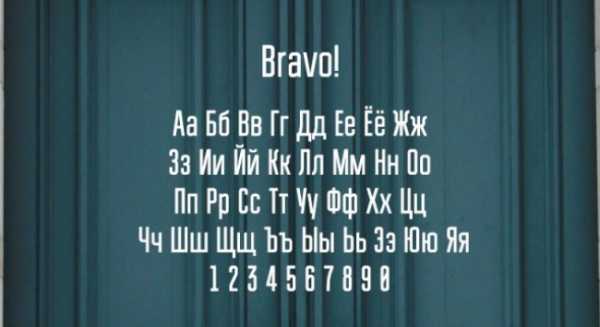
Yanone Kaffeesatz
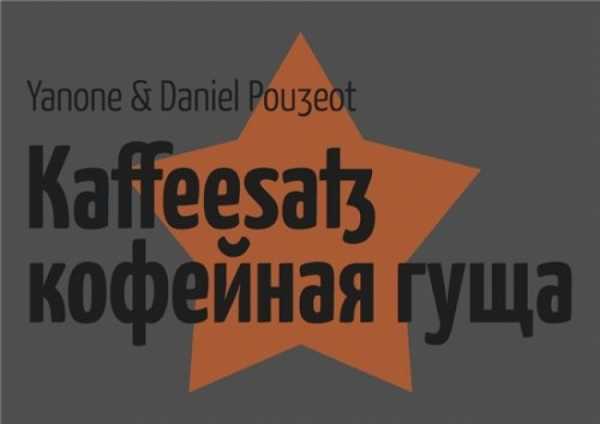
BadScript
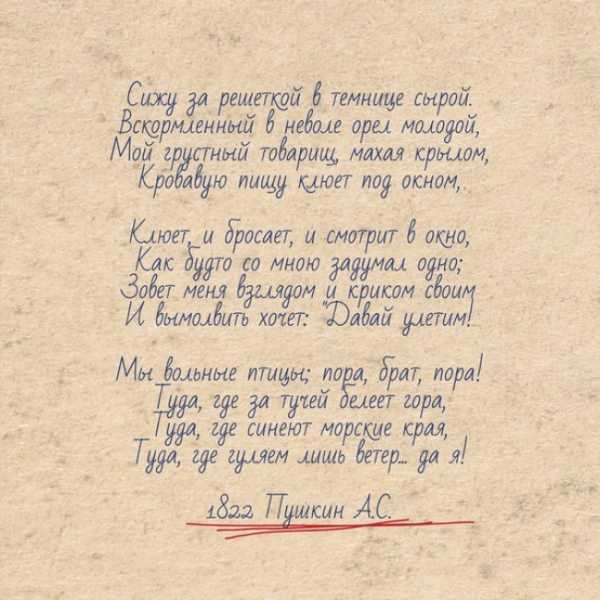
Nord
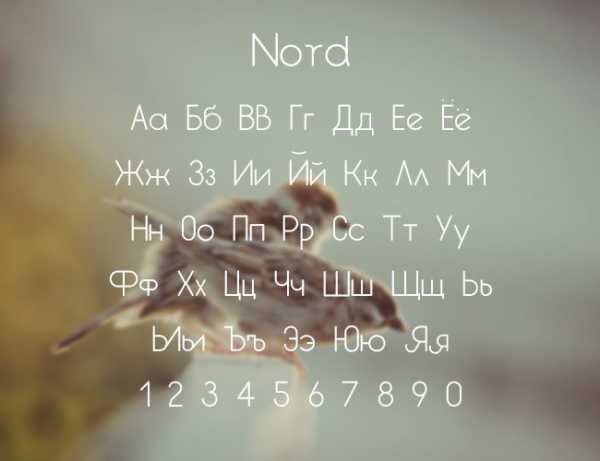
Intro Condensed
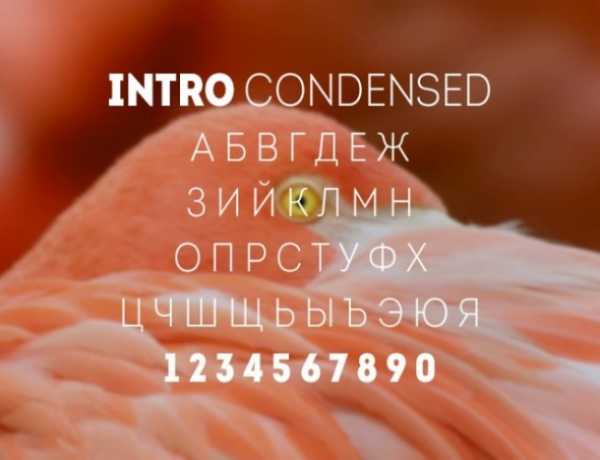
Ropa Sans
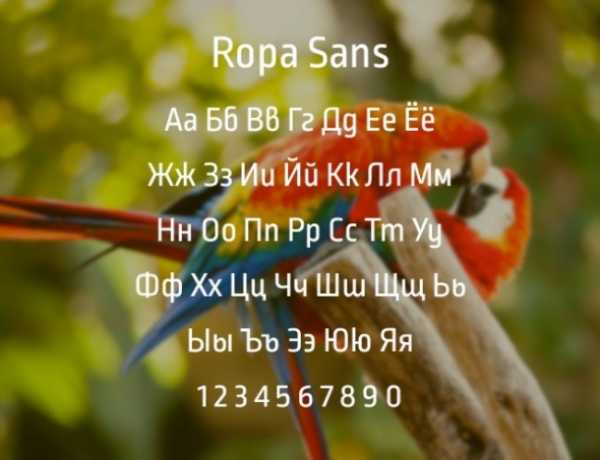
Centar Sans
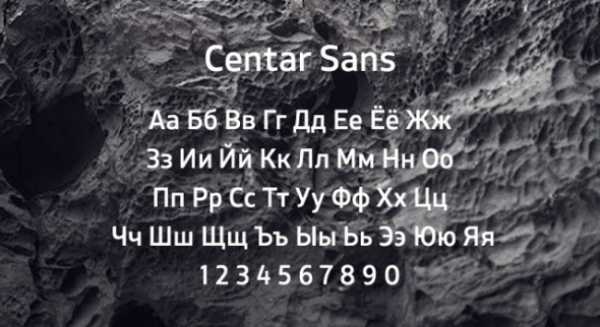
Lighthaus
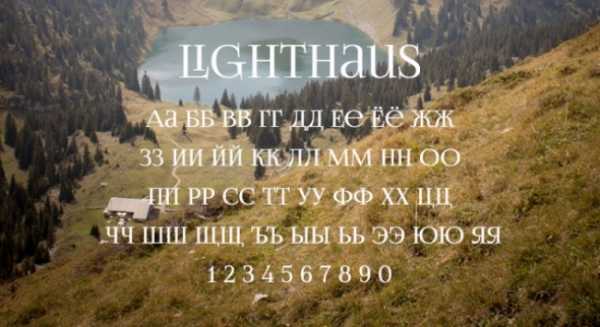
Старомосковский
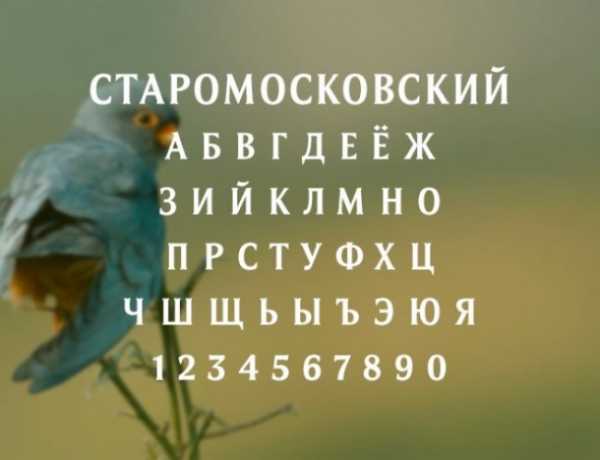
Uni Sans
Clinica Pro
LeHand
Топ-12 Самых Популярных Шрифтов Всех Времен — Секреты Успеха
Шрифты стали неотъемлемой частью «чтения-письма» общества на протяжении многих веков, а сейчас они превратились в цифровую эпоху книгопечатания и дизайна, где шрифты играют еще более важную роль, нежели это было раньше. Шрифты в значительной степени влияют на то, как ваш типографский материал выглядит и чувствует себя в аудитории, поэтому важно тщательно выбирать шрифт для печати, публикации, веб-разработки и выполнения других задач. Ниже мы собрали список самых1. Helvetica (Макс Мидингер, 1957 г.)
Helvetica, пожалуй, самый известный шрифт на планете. Первоначально разработанный швейцарским дизайнером Максом Мидингером в 1957 году, этот классический шрифт используется во всем мире с момента своего рождения в 1950-х годов до сегодняшнего дня. Его огромная популярность может быть зачислена на тот факт, что он по-прежнему выглядит современно, просто, а также универсально и надежно, как по-швейцарски.2. Times (Стэнли Морисон, 1931 г.)
Уильям Смит-Линц, менеджер лондонской ежедневной газеты «The Times» в 1929 году, который был не впечатлен качеством печати своей газеты, услышал о столь уважаемом типографе Стэнли Морисоне. Впечатленный аргументами Морисона, газетчик нанял его, чтобы перепроектировать свою газету, и в 1931 году Морисон дал газете свой новый шрифт, Times New Roman, который заменил своего предшественника Times Old Roman. С тех пор он является одним из самых популярных шрифтов, используемых во многих издательских материалах и новостных печатных изданиях.3. Akzidenz Grotesk (Brethold Type Foundry, 1896 г.)
Akzidenz Grotesk повлиял на широкий спектр других популярных шрифтов, таких как популярные Helvetica и Frutiger, и был впервые выпущен в 1896 году в Германии в Brethold Type Foundry. Шрифт обрел новую высоту популярности после того, как был заново открыт с более широким значением и в разных вариантах под руководством Гюнтера Герхарда Ланге в 1950-х годах.Это может быть интересно: Раскрыты основные секреты миллиардеров
4. Gotham (Хоуфлер и Фрер Джонс, 2000 г.)
Выпущенный в 2000 году Gotham является адаптацией 20-го века, подписанный американским производителем «Готика». За последние 16 лет он стал широко популярен среди дизайнеров с чистыми и современными взглядами. Популярность шрифту принесла история кампании Экс-Президента США Обамы, в которой использовался шрифт Gotham во время выборов 2008 года.5. Bodoni (Бодони, 1790 г.)
Джамбаттиста Бодони разработал этот шрифт с засечками в конце 18-го века во дворце герцога Фердинанда Бурбон-Парма, который сильно восхищался ремеслом Бодони и дал ему разрешение на строительство частной типографии при своем дворце. Bodoni уже был широко популярным шрифтом, когда в 1920-е годы Моррис Фуллер Бентон возродил его для АТФ с подробным акцентом на различные значения. Фильм «Славные парни» использовал этот шрифт на своих плакатах.6. Futura (Пол Реннер, 1927 г.)
Futura был разработан Полом Реннером в 1920-е годы в Германии, и с момента своего рождения Futura стал эталоном геометрических шрифтов со своими замечательными формами в течение уже более 80 лет. Этот современный шрифт оказал влияние на многих дизайнеров, и в настоящее время широко используется в бизнес-вывесках и рекламах. Фольксваген использует его в качестве шрифта заголовка в течение многих лет.7. Rockwell (Monotype Foundry, 1934 г.)
Rockwell является одним из наиболее известных примеров густоты засечек в шрифтах с толстыми, острыми засечками и различными отчетливыми геометрическими фигурами. Разработанный дизайнерским отделом Monotype Foundry в 1934 году, Rockwell прежде всего стал популярен как выставочный шрифт, а также известен при добавлении элегантности в любую часть рисунка.8. Franklin Gothic (Моррис Фуллер Бентон, 1903 г.)